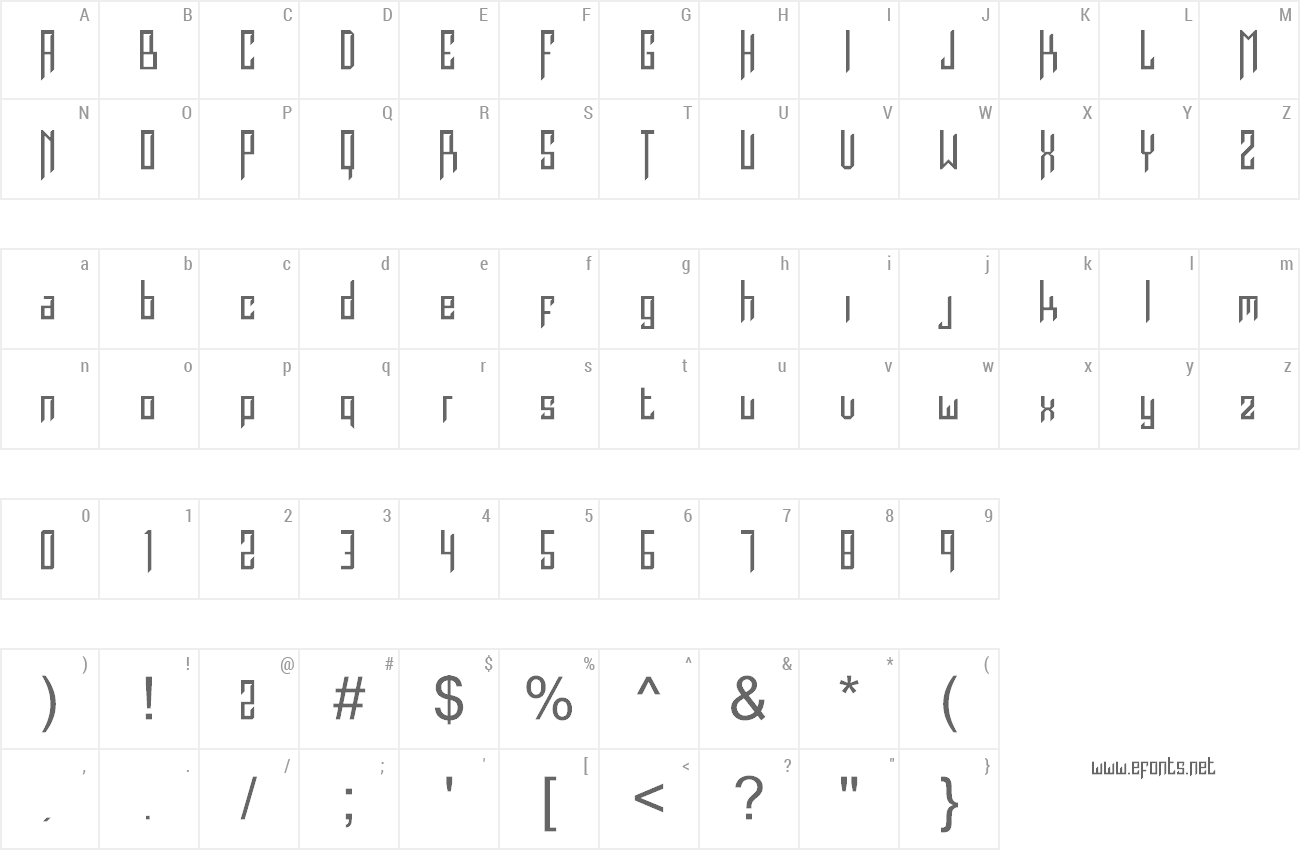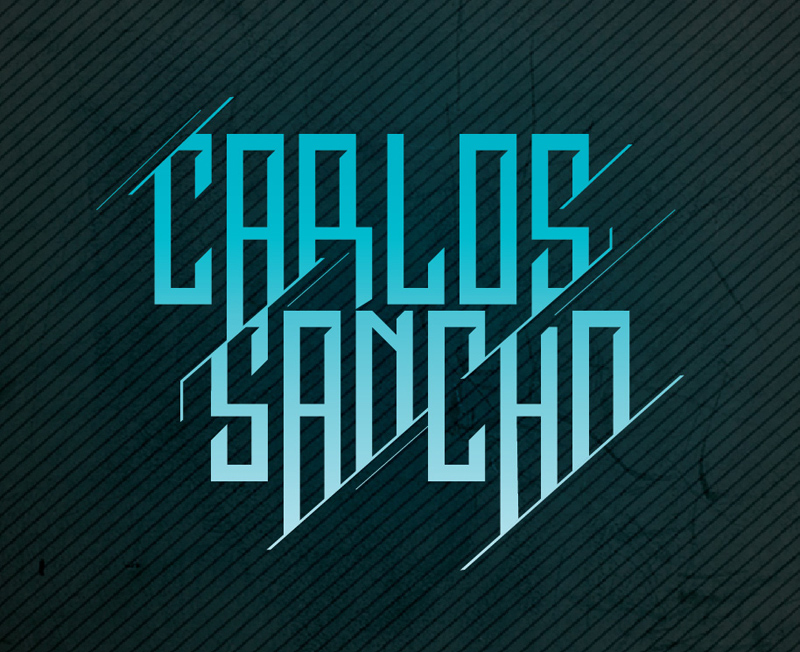
Preview and download Burdeles Font. Created by Burdeles in Gothic Modern styles with Free for personal use license.
| Note by Burdeles | |
| La burdeles, de aspecto filoso, alargado y rockero, usarla preferentemente para frases muy cortas. Que la disfruten! |